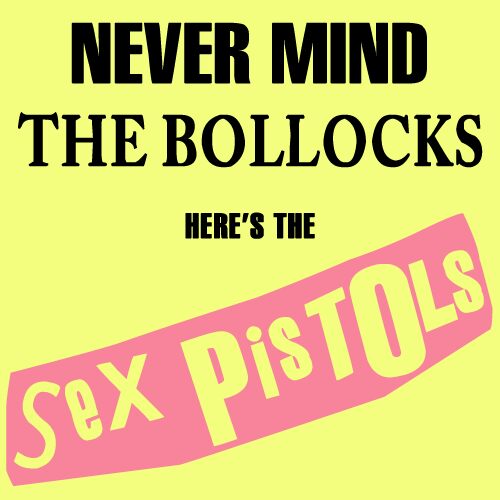
Sex Pistols to darmowy, punkowy krój typu display, oddający ducha wycinanek z ulotek końca lat 70. Litery łączą wydłużone krzywizny, ostre kąty i nierówne proporcje, dzięki czemu cały font sprawia wrażenie celowo niechlujnego, niczym nagłówki złożone z podartych kawałków plakatów.
Idealnie pasuje do plakatów muzycznych, zinów, okładek płyt, klimatu klubowego i buntowniczej grafiki, gdzie surowa energia fontu wypada lepiej niż idealna czystość. Używaj go w krótkich nagłówkach, tekstach na okładki, tytułach czy surowych logotypach, zwłaszcza gdy zależy Ci na efekcie improwizacji i lekkiej konfrontacji.